在香港的大街小巷里,你是否被中国传统书法风味的广告招牌字体所吸引?跟内地琳琅满目的现代广告艺术字不一样,满街头颇具中国传统书法风味的广告招牌字体确是香港别具一格的特色。
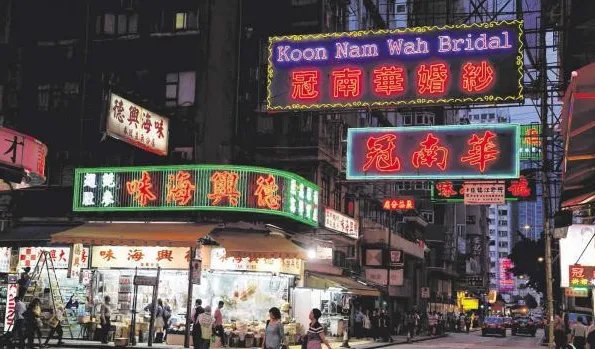
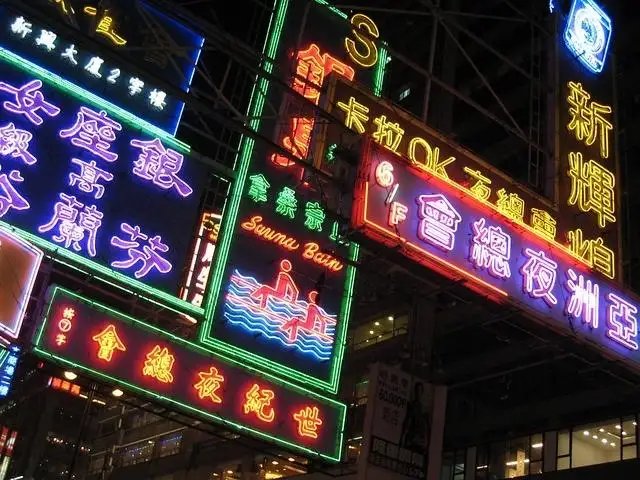
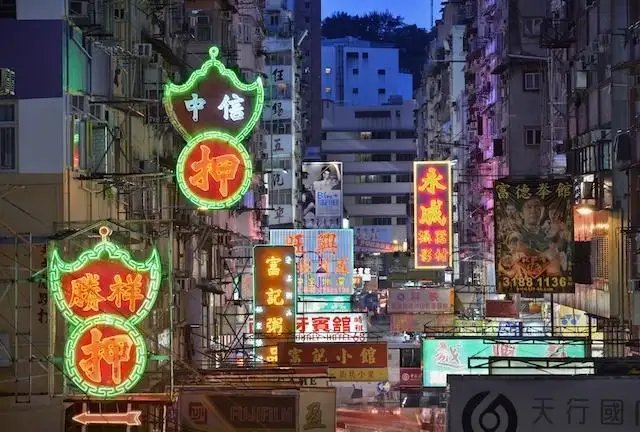
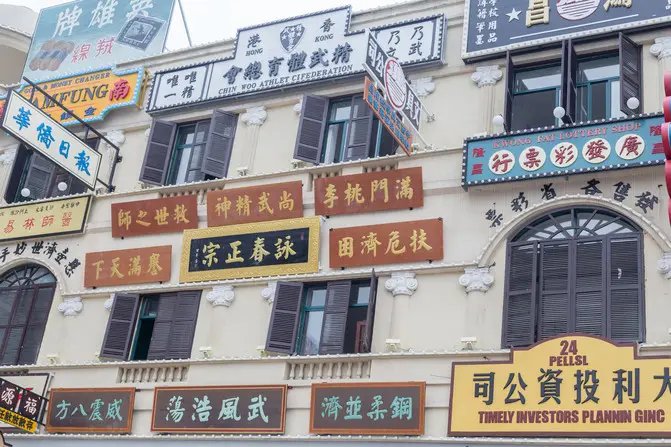
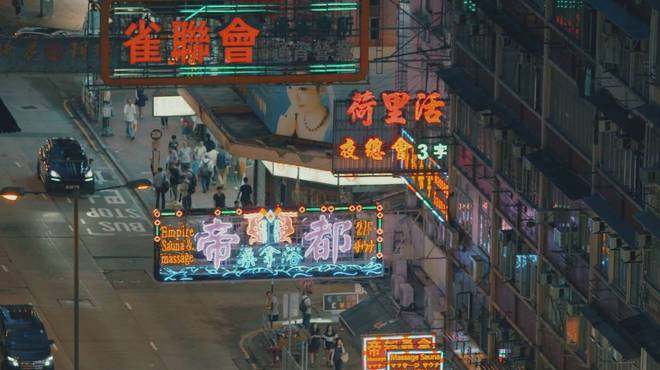
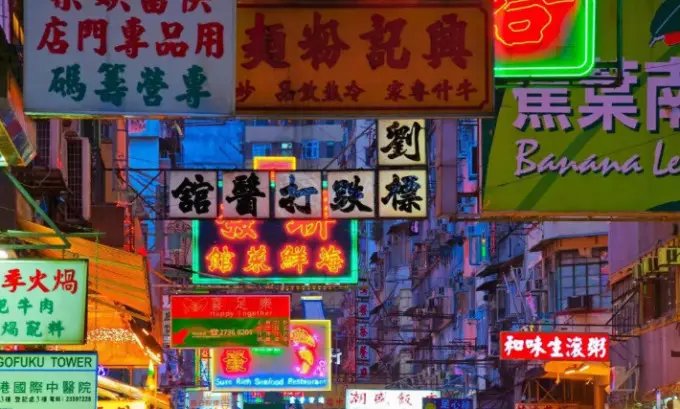
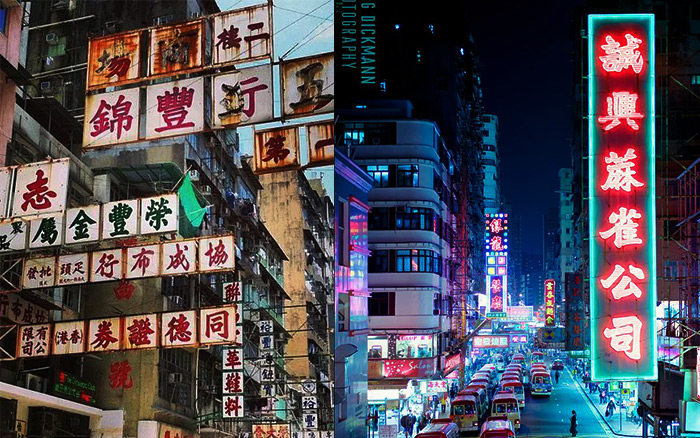
广告招牌字并不是单纯追求美学,也讲求辨认程度。上世纪40年代开始,香港流行商住混合式大厦,人们在里面单位搞小生意,况且香港的街道密集,要从茫茫字海突围而出,就由字体、颜色入手才能提高辨识度。
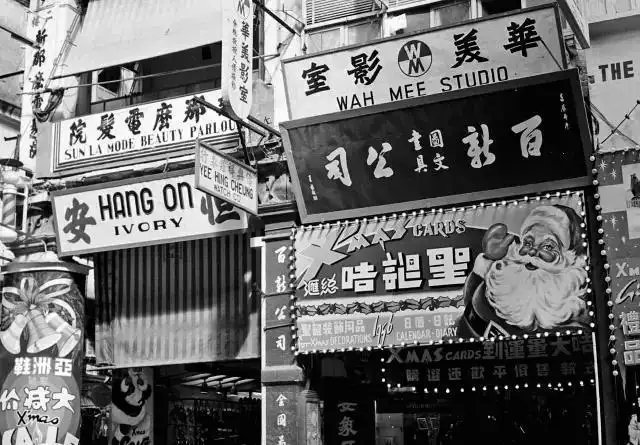
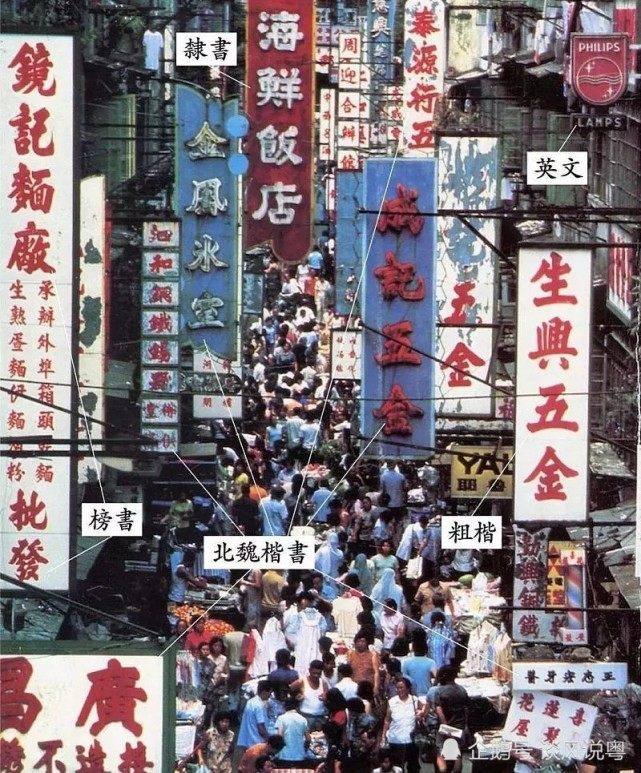
香港街头成千上万的书法招牌,展示着永恒的中国印记。这些隽永、遒劲、优雅或秀丽的中国书法字体,成为了香港中年、老年人的集体回忆,也曾在回归前时刻提醒英国殖民者:这里是中国的土地,中国人民、中国文化、两岸情感生生不息。